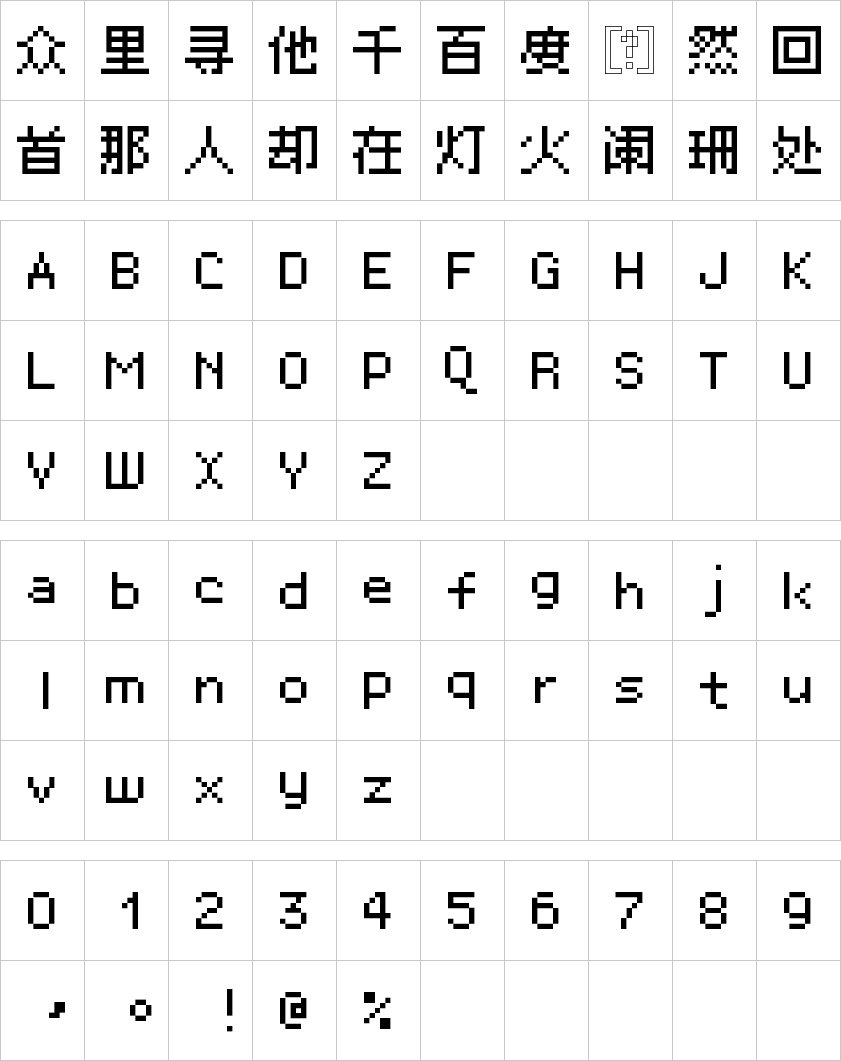
精品点阵体9×9
精品点阵体9×9字体在线预览效果
精品点阵体9×9字符映射图
《精品點陣體7×7 (BoutiqueBitmap7x7) 》是一款基於美咲フォント改作的字型,目的為適合在繁體中文環境中使用。我們改正了一些標點符號、日本習慣寫法、增加大量字符,使字型使用更方便! 這是一款帶有極強烈的點陣風格的字型,非常適合用在像素畫、遊戲相關主題等等。